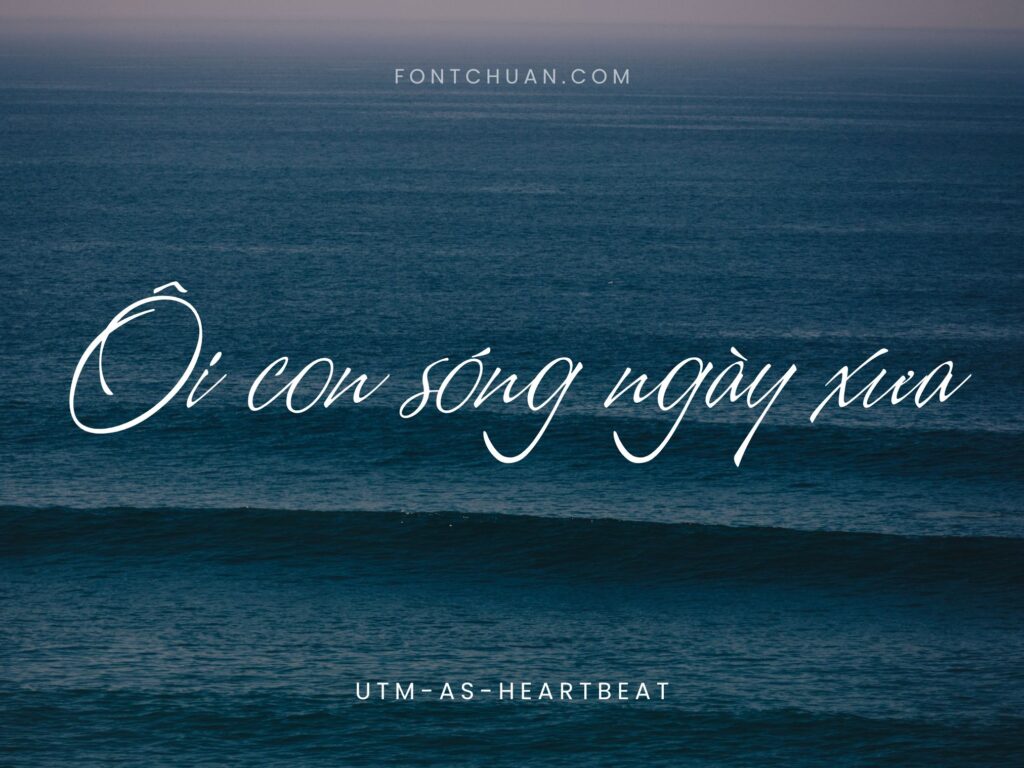
Font UTM A&S Heartbeat Việt Hóa
UTM A&S Heartbeat là một Font Handwritten mang phong cách hiện đại và đầy cảm xúc, lấy cảm hứng từ nhịp đập của trái tim. Font này đã được Việt hóa bởi Đinh Kiên, hỗ trợ đầy đủ tiếng Việt cùng hơn 100 ngôn ngữ khác. Đây là một trong những font được thành viên Font Chuẩn sưu tầm và chọn lọc nhằm đáp ứng nhu cầu đa dạng của cộng đồng thiết kế.
UTM A&S Heartbeat có cấu trúc chữ với các nét uốn lượn mềm mại và tự nhiên, mang hơi thở của Font Script nghệ thuật, tạo cảm giác gần gũi và thân thiện. Font này phù hợp cho các ứng dụng như thiết kế thiệp mời, tiêu đề, logo và các ấn phẩm in ấn yêu cầu sự tinh tế và cá nhân hóa. Các ngành nghề như quảng cáo, thiệp cưới, giáo dục và ẩm thực có thể tận dụng UTM A&S Heartbeat để tạo điểm nhấn độc đáo trong thiết kế.